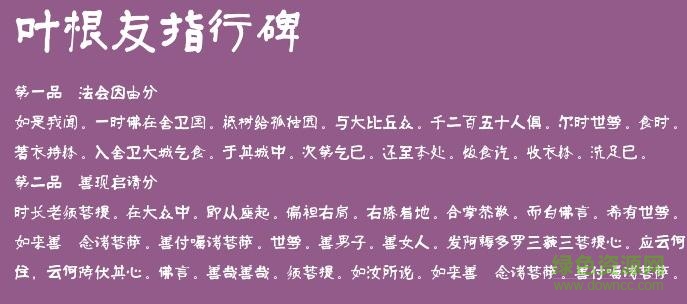
葉根友指行碑字體是一款葉根友字體出品的簡體碑體字體,小編為大家?guī)砻赓M(fèi)下載地址,這款字體藝術(shù)性較高,適合用于廣告設(shè)計(jì),歡迎大家來綠色資源網(wǎng)踴躍下載哦!
葉根友指行碑是一款用指尖書寫的字體。有一種輕描淡寫的韻味,非常的文雅好看,是葉根友字體里面比較大方得體的了。